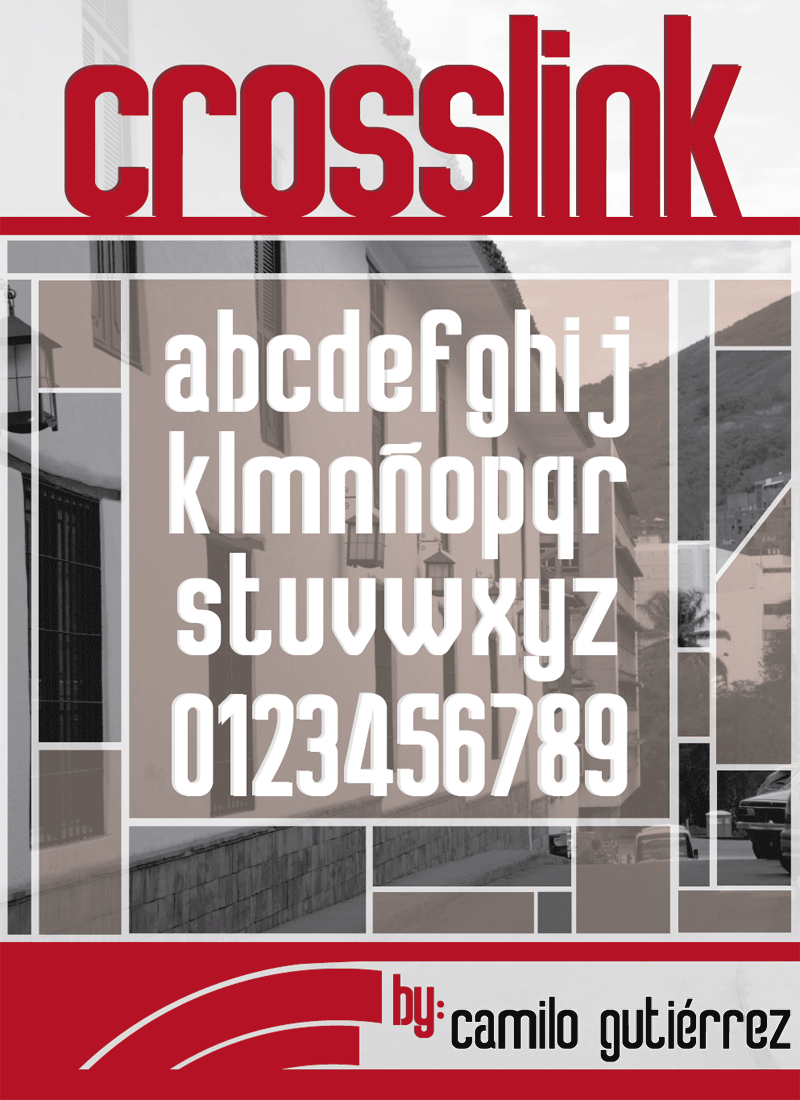
Font name: | Crosslink |
Author: | Camilo Gutiérrez |
Note by Camilo Gutiérrez | |
Esta fuente tipográfica está inspirada en el Estilo Internacional Suizo, combinando de esta manera las características principales de este movimiento. |